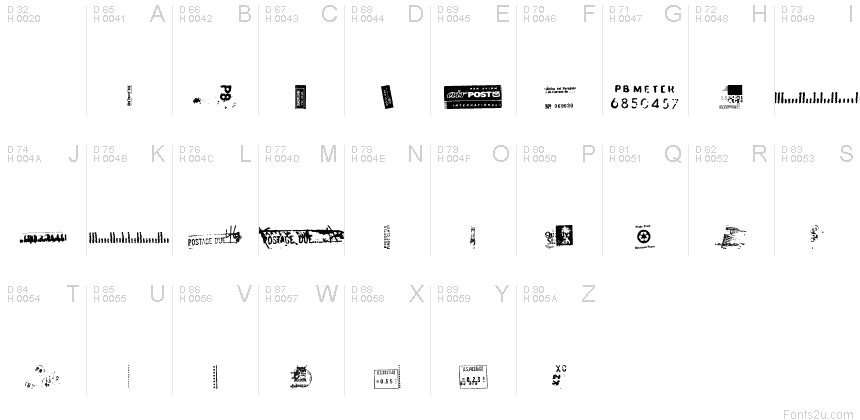
Dead Letter Office Seventeen di Andi Jones è un font dingbats gratuito dallo stile vissuto, intriso di fascino postale. Con le sue etichette ritagliate, i timbri rovinati e i segni della posta aerea, sembra uscito da un centro di smistamento dimenticato, donando ai tuoi lavori quel look inchiostrato e autentico senza dover scansionare vecchi documenti.
Dead Letter Office Seventeen aggiunge istantaneamente texture a mail art, flyer punk, collage, fanzine, pagine di scrapbook, etichette e copertine di album. Questo font gratuito è ideale per accenti o sovrapposizioni piuttosto che per il corpo del testo; abbinalo a un carattere typewriter o a un sans serif pulito per esaltare al meglio il suo aspetto grezzo da timbro a inchiostro.